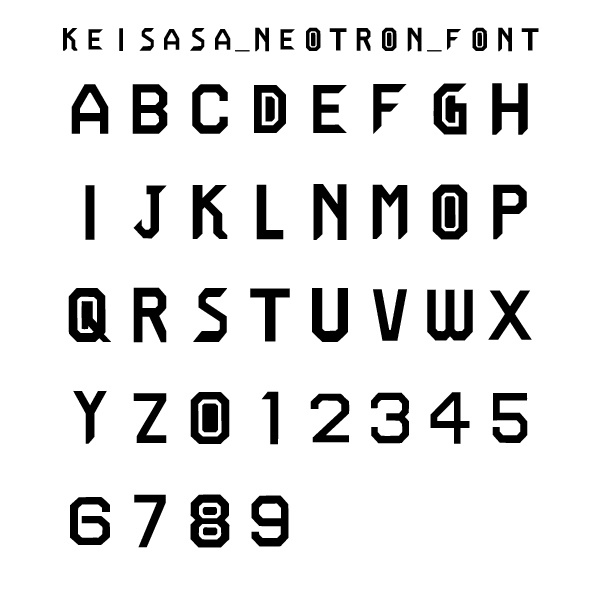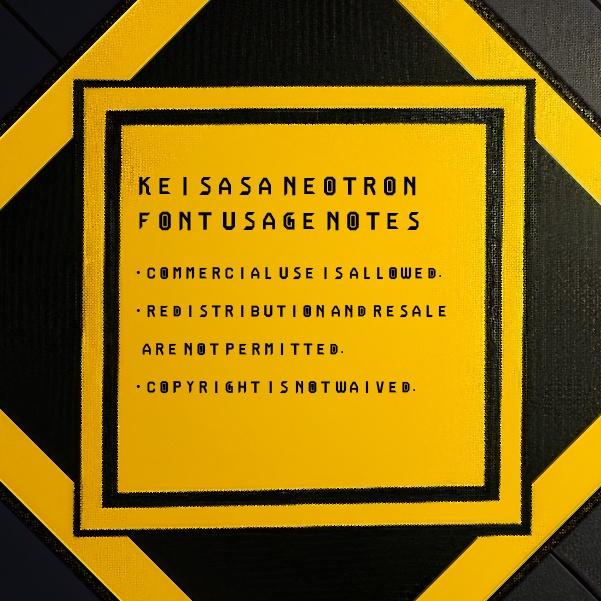
【商用可】Keisasa Neotron Font︱ メカニカルな印象を持つ近未来フォント
収録文字:A–Z(大文字)、0–9 対応形式:TTF 商用利用可/再配布不可 制作:sasasasaya / ksuke sasaki 無機質で幾何学的なフォルムを持つ、サイバーパンク風のデジタルフォント。 構造的な角と直線が織りなす文字は、SF・ゲームUI・未来都市をテーマにしたデザインに最適です。 タイトルロゴやテック系のブランドロゴ、アニメ・映画のプロモーションにもフィットします。 A geometric, cyberpunk-style display font with a structured and mechanical look. The clean edges and straight lines make it perfect for sci-fi titles, futuristic interfaces, and branding that evokes a high-tech aesthetic. Ideal for game titles, digital posters, or any design that needs a bold, synthetic edge.